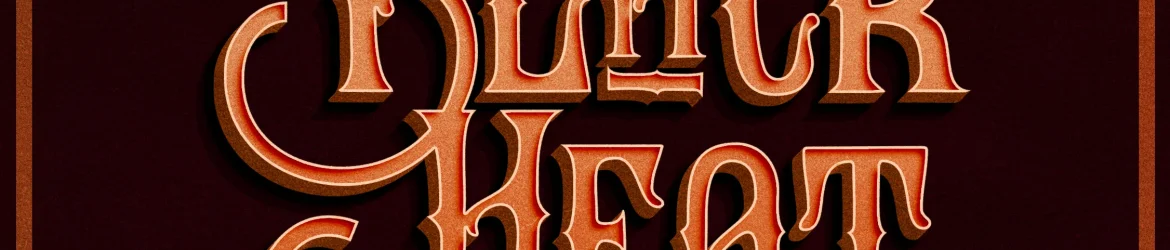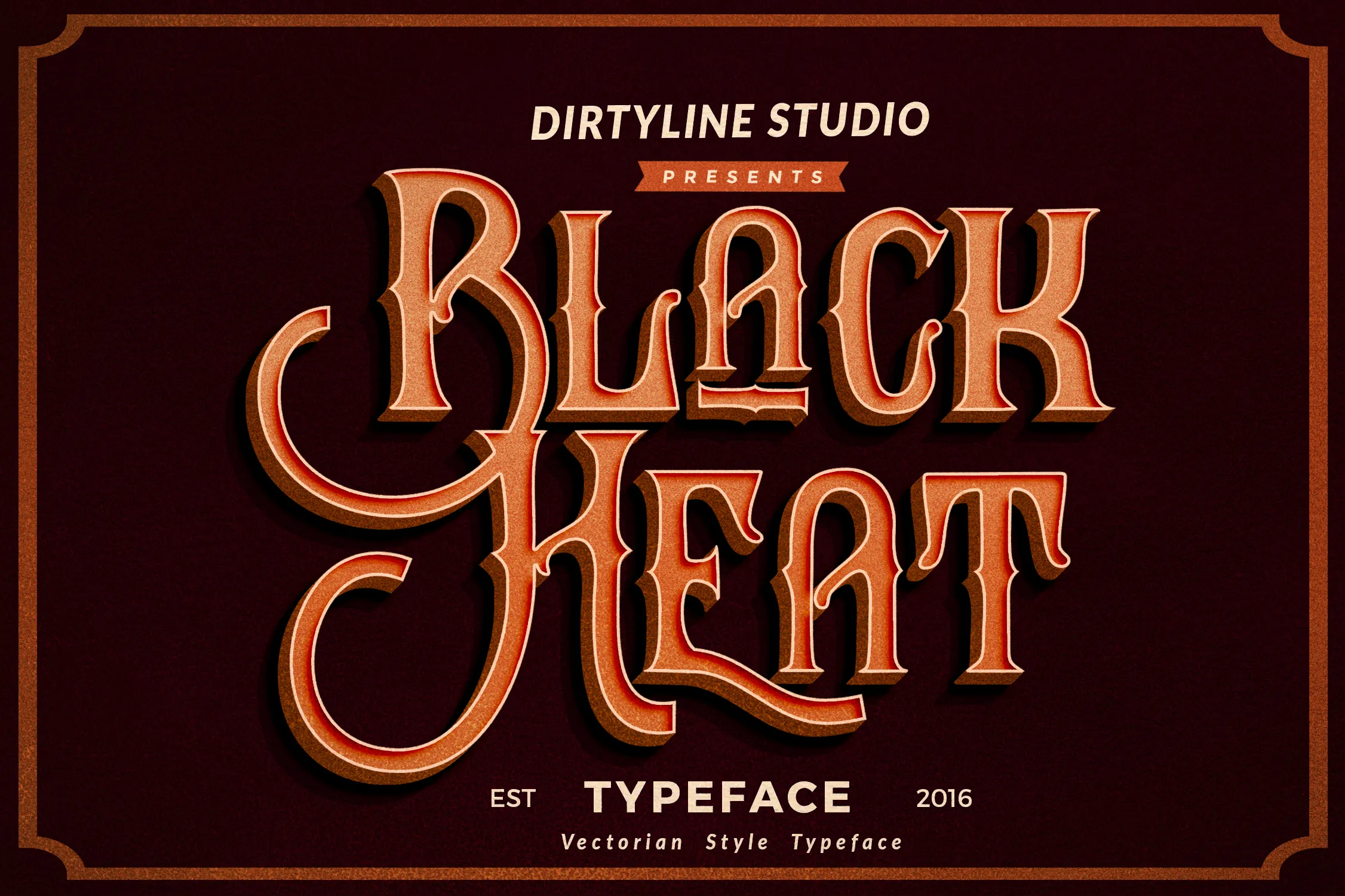
Black Heat Font – Fonte Grátis
Black Heat Font
A fonte ‘Black Heat’ é uma inovação na categoria das fuentes góticas que traz modernidade e elegância ao conjunto vintage dos traços. Desenvolvida pelo designer Hamilton, essa fonte apresenta características decorativas além de um deslumbrante desenho da linha de base que flutua como dança em seu próprio tempo. Perfeita para invitações, cartas de cumprimentos e materiais de marca, a ‘Black Heat’ se destaca por suas nuances e detalhes meticulosamente criados. Suas aplicações abrangem não apenas cartões de visita e placas comerciais, mas também citações em ambientes corporativos, posters que chamam atenção nos eventos sociais e até mesmo mensagens de texto digital. Com a sua composição elegante e estilo gótico, essa fonte é uma escolha ideal para quem busca um toque moderno em seus materiais gráficos. Ela traz à tona o fascínio pelo passado sem perder seu caráter inovador para atender às necessidades de design contemporâneas.